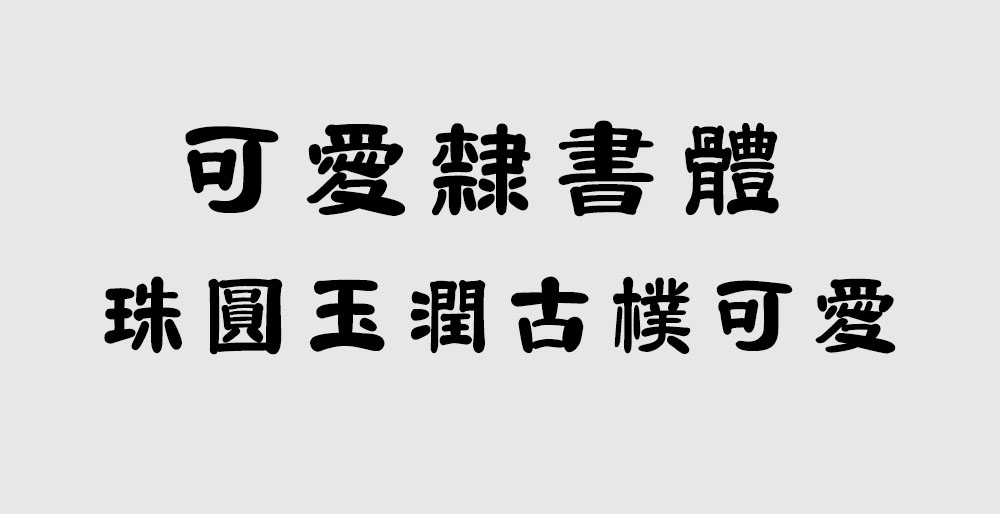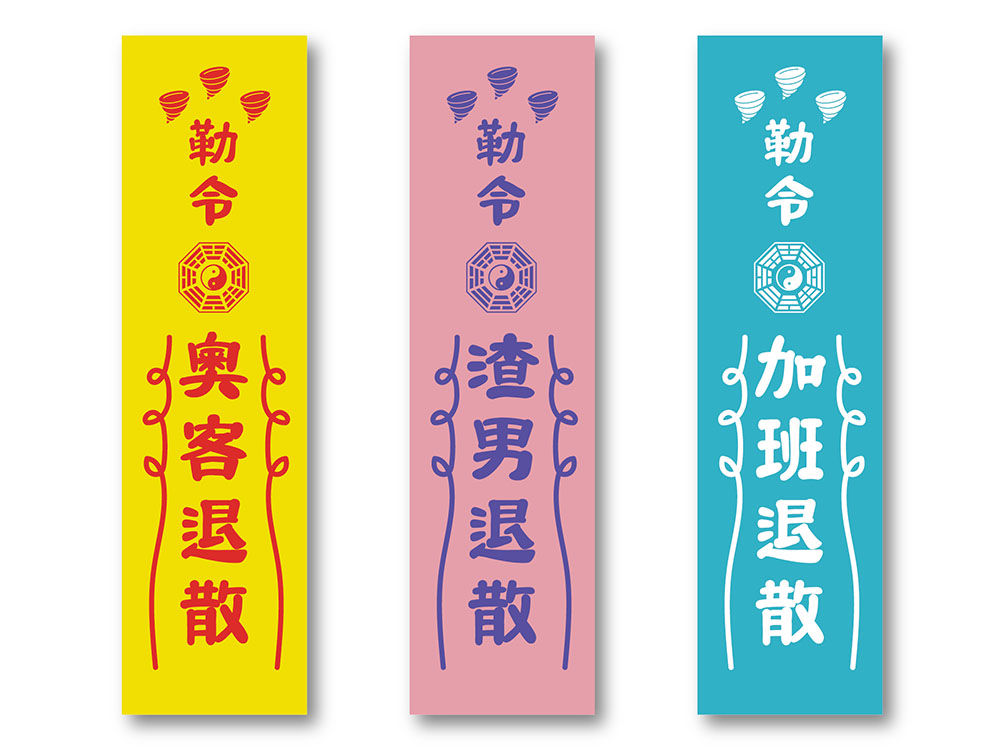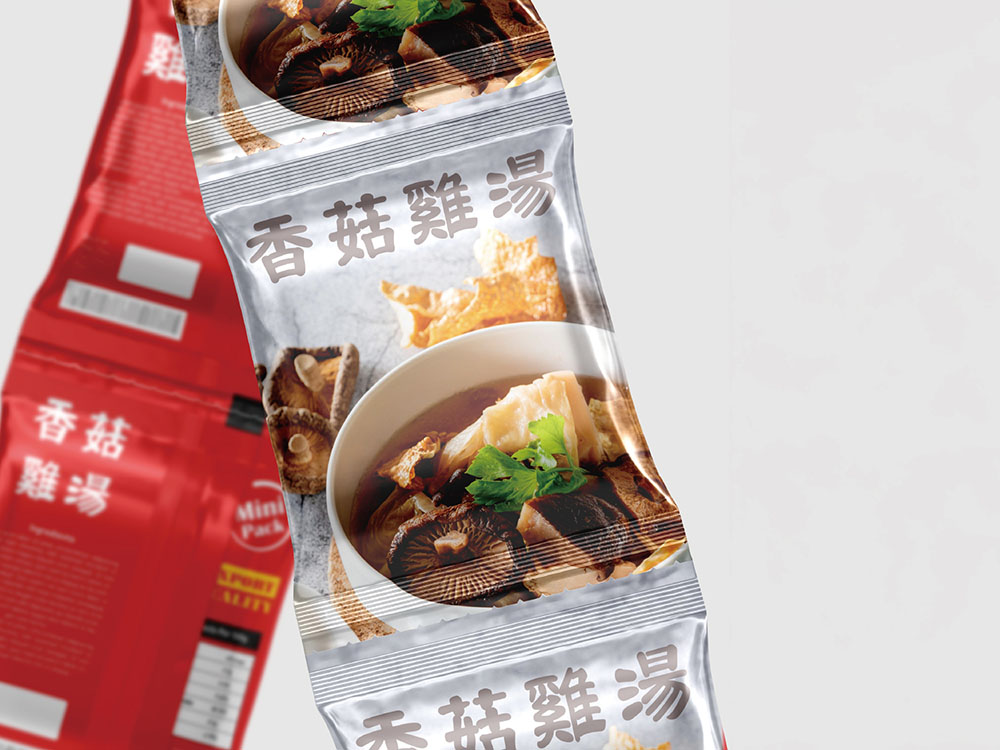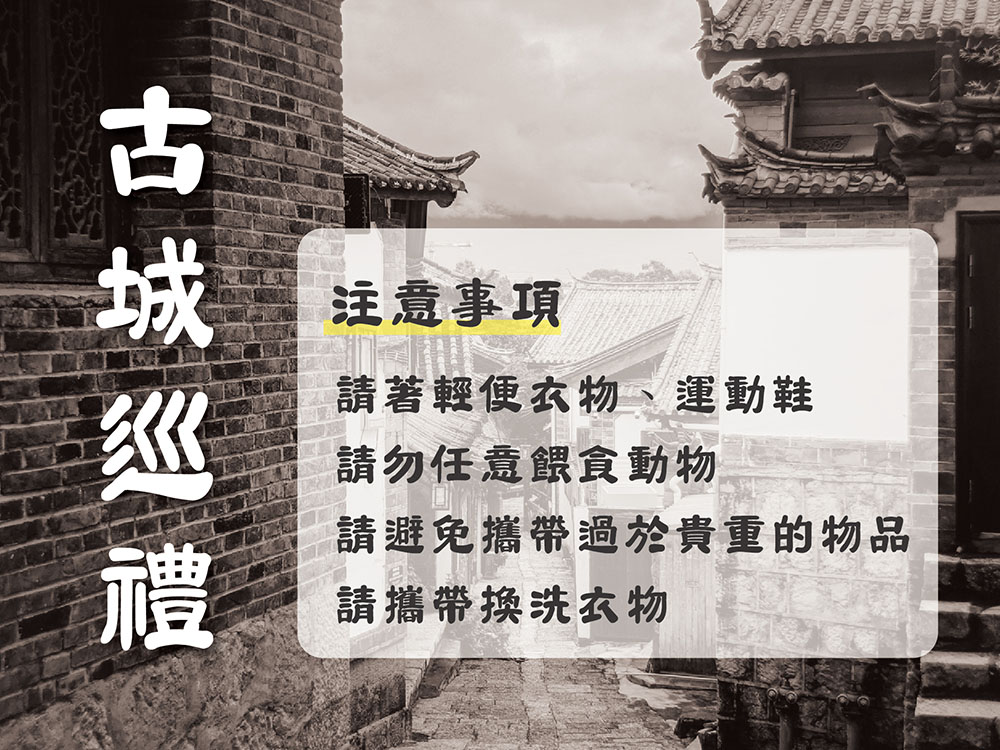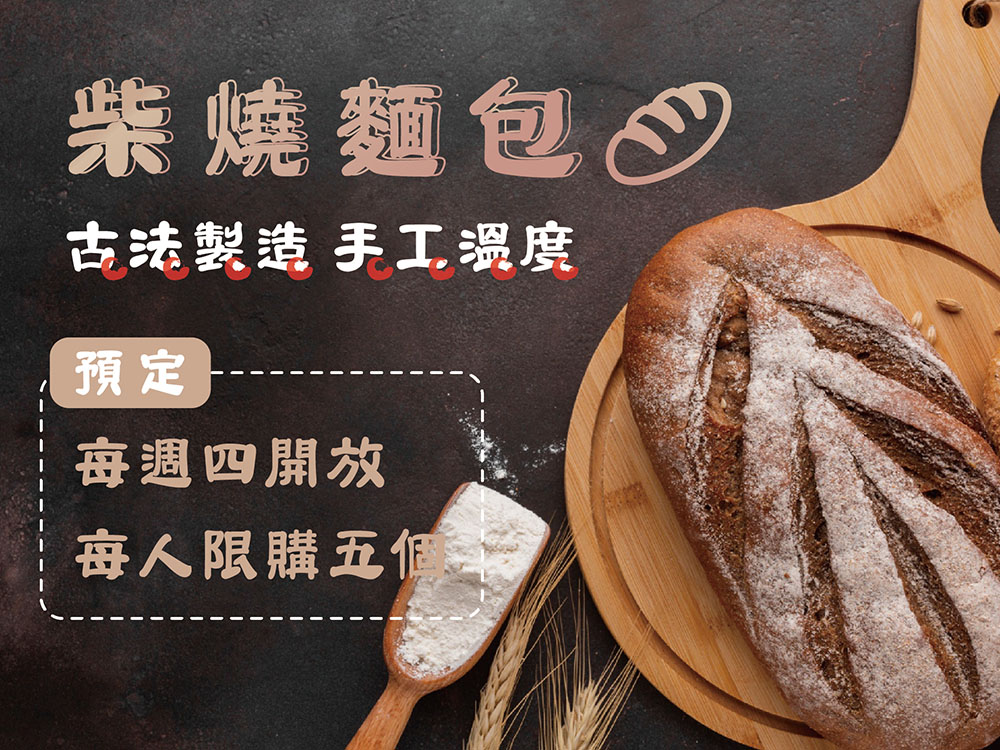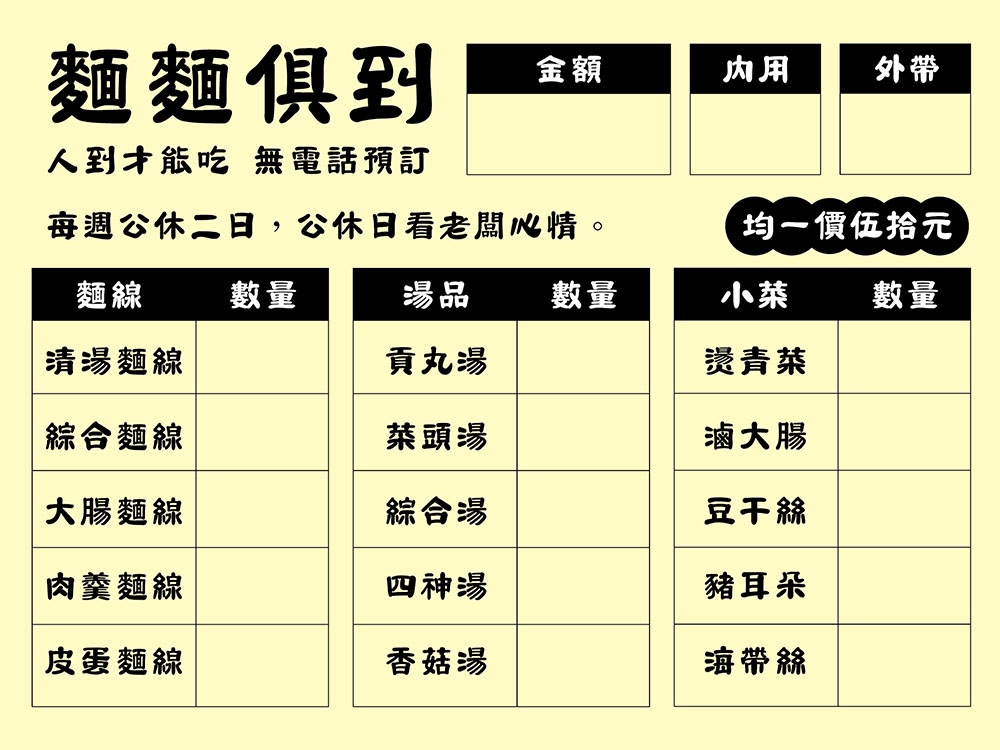
可愛隸書體大約有9400個字(包括歐文、數字、符號、日文片假名及平假名)。
可愛隸書體 – 珠圓玉潤古樸可愛
橫豎之間顯端莊,撇捺之間藏靈動。
珠圓玉潤的外形,獨特而可愛,
厚重古樸的寫法,盡顯隸書之美。
一款將傳統隸書與現代可愛風格結合的字體。
撇捺靈動,橫豎端莊;字形珠圓玉潤,厚重古樸中帶有獨特可愛感,既保留隸書筆法,又適合日常使用。
可愛隸書體在保留傳統特徵的同時,將筆畫調整得更圓潤親切,粗細過渡自然,閱讀舒適。
*適用場景*
- 節慶設計(春聯、賀卡、包裝)
- 文創產品(銘文、海報、筆記本)
- 數字媒體(YouTube字幕、社交媒體圖文)